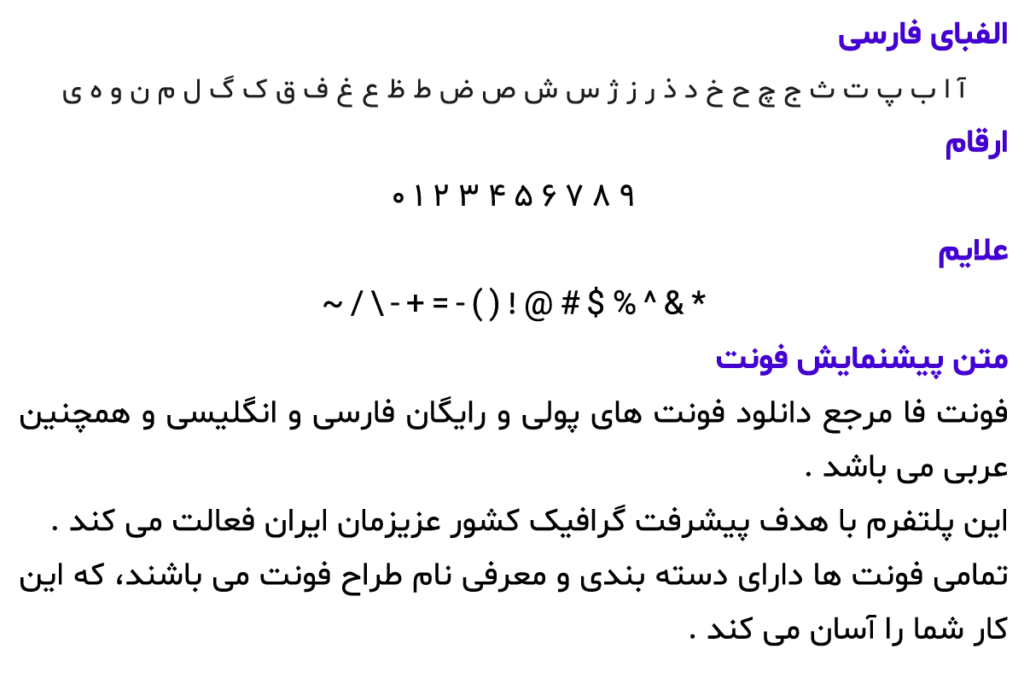
فونت فارسی شبنم – Shabnam
طراح فونت: صابر راستی کردار نوع فونت: فونت طراحی وب و فونت متن و فونت هندسی
پیشنمایش فونت شبنم
توضیحات و معرفی فونت شبنم
فونت فارسی شبنم ( Shabnam 5.0.1 ) از مجموعه فونت های آزاد می باشد، همینطور نوع فونت طراحی وب و متن و هندسی می باشد.
آخرین نسخه فونت زیبای مرتبط توسط شادروان صابر راستی کردار طراحی و ساخته شده است.
همینطور فونت شبنم در 5 وزن سبک و پر رنگ و نازک و متوسط و معمولی است.
در لیست زیر می توانید وزن های این فونت زیبا را ببینید.
- Shabnam Light
- Shabnam Bold
- Shabnam Thin
- Shabnam Medium
- Shabnam Regular
در اینجا شعر زیبای وطن را می توانید در قالب تایپ فیس شبنم ببینید و لذت ببرید…